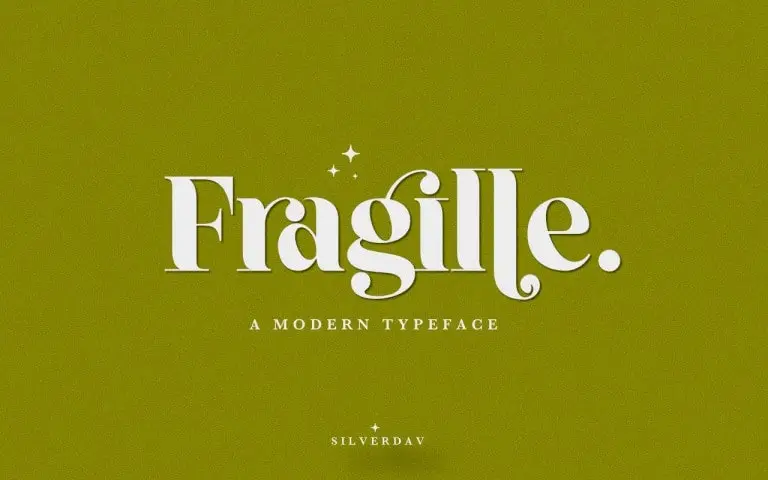
Fragille Serif Font – Download Grátis
A Fragille Serif Font é uma elegante fonte moderna e minimalista criada pelo Silverdav Studio. Este é um tipo de letra com linhas contrastantes e detalhes finos que traz beleza a qualquer projeto. Suas características especiais, ornamentações e suporte multilíngue tornam este tipo de escrita perfeita para criações profissionais como logotipos, marcas de capa de revista, cartões de casamento ou convites. Seu formato também é ideal para se destacar em cabeçalhos e projetos com grande tamanho de fonte. Fragille adere ao encanto eterno da beleza clássica e aos arredondamentos divinos, oferecendo um estilo elegante a qualquer projeto. Com certeza faria um diferencial notável em qualquer trabalho de design.